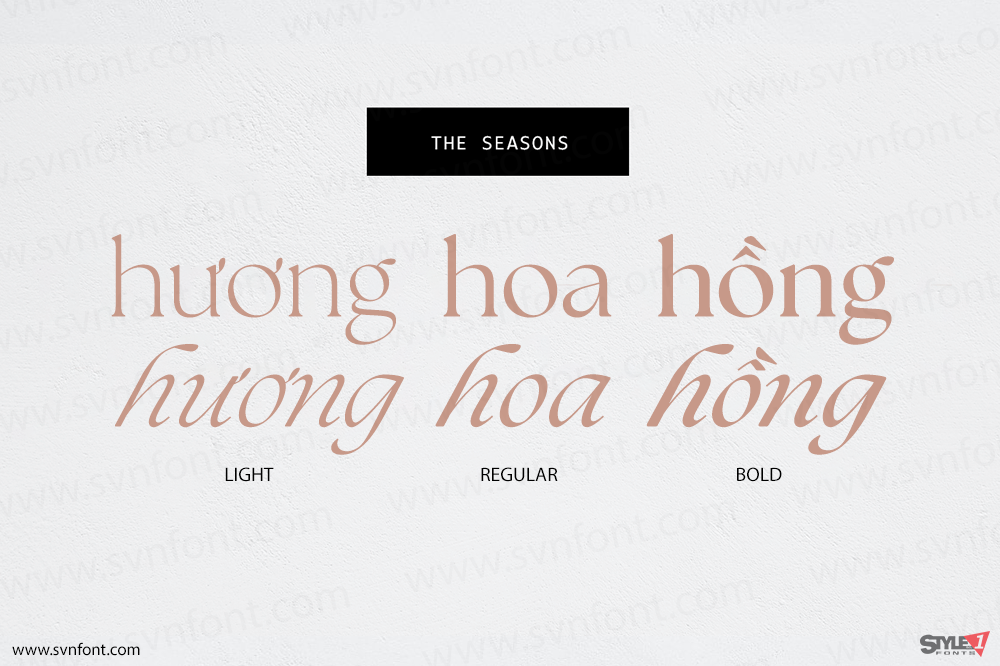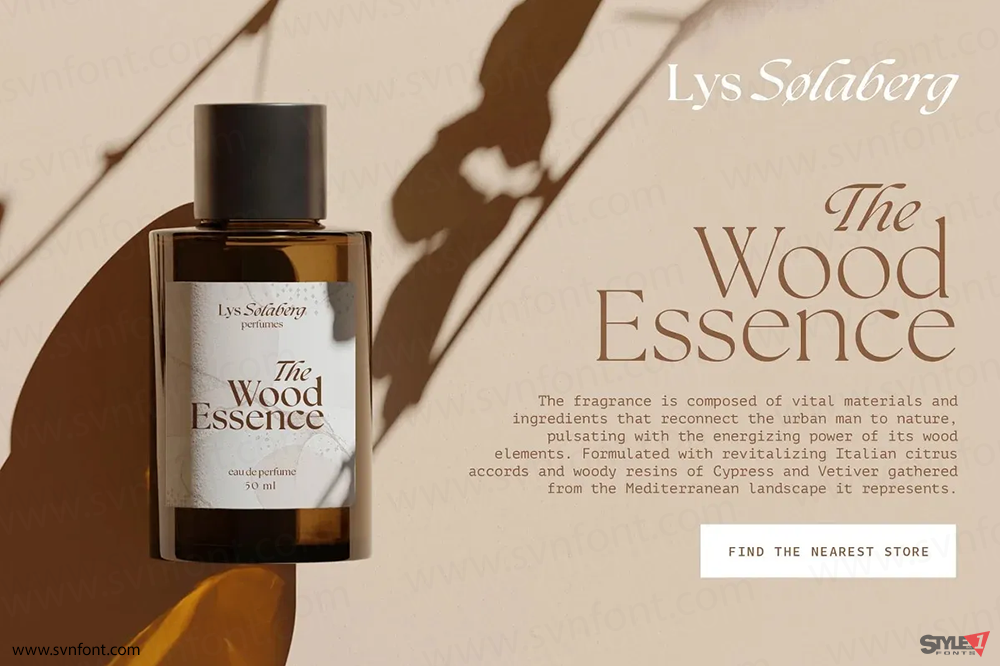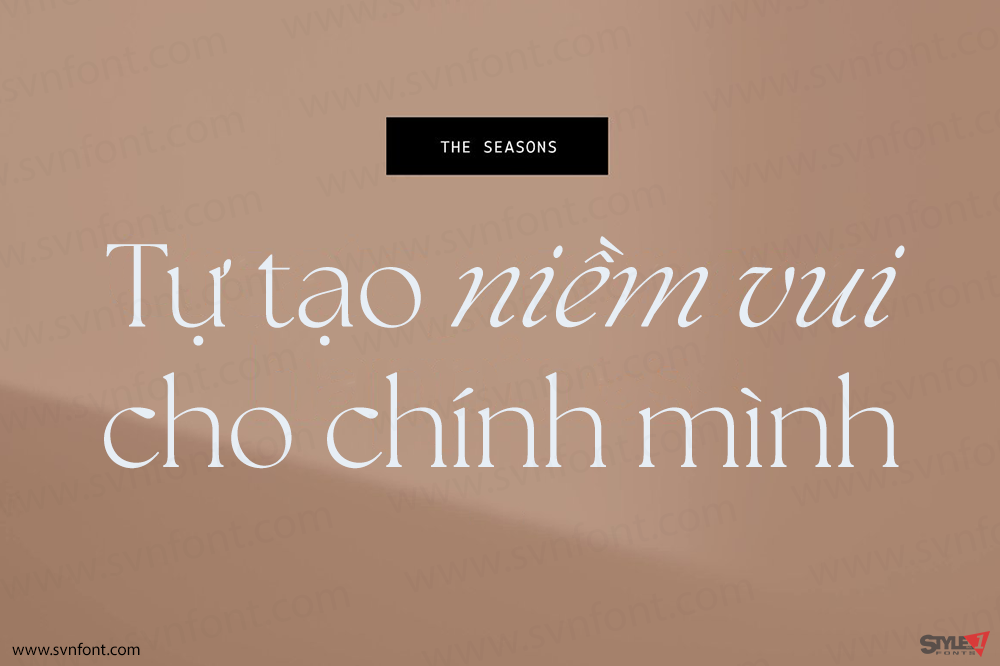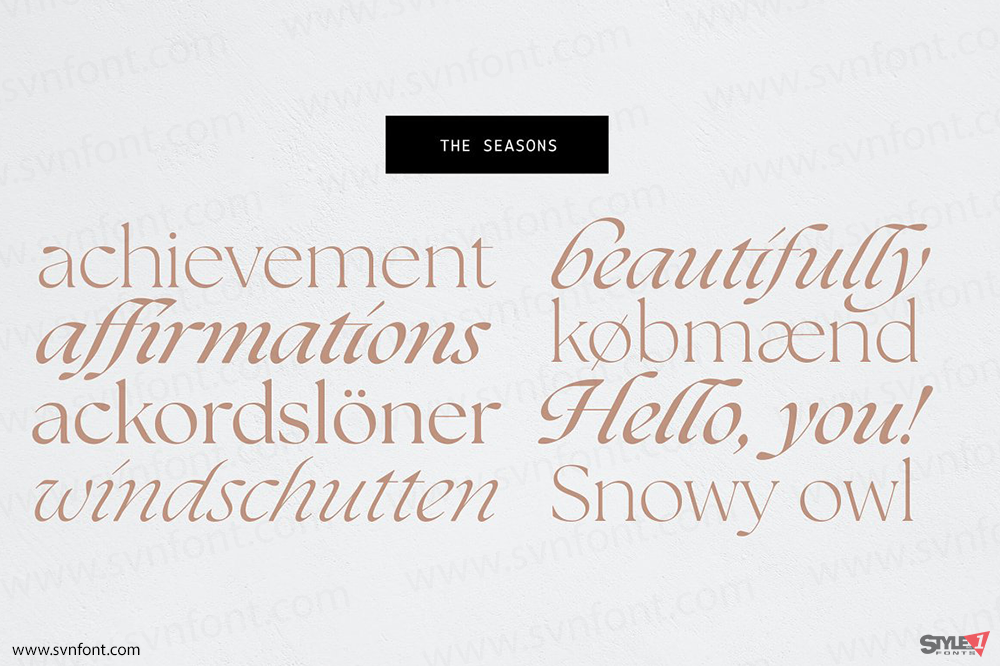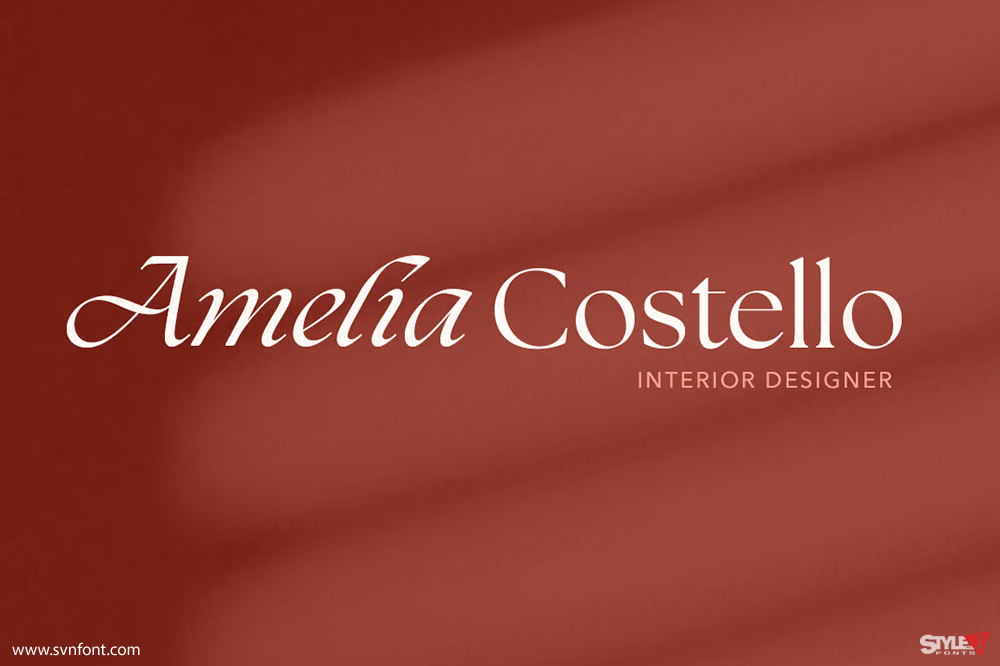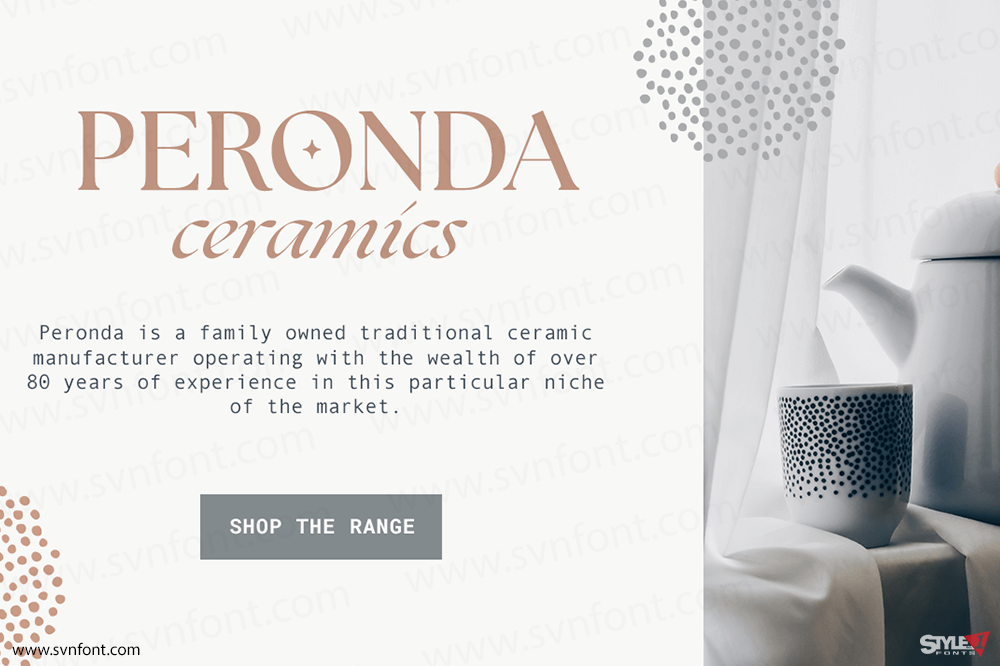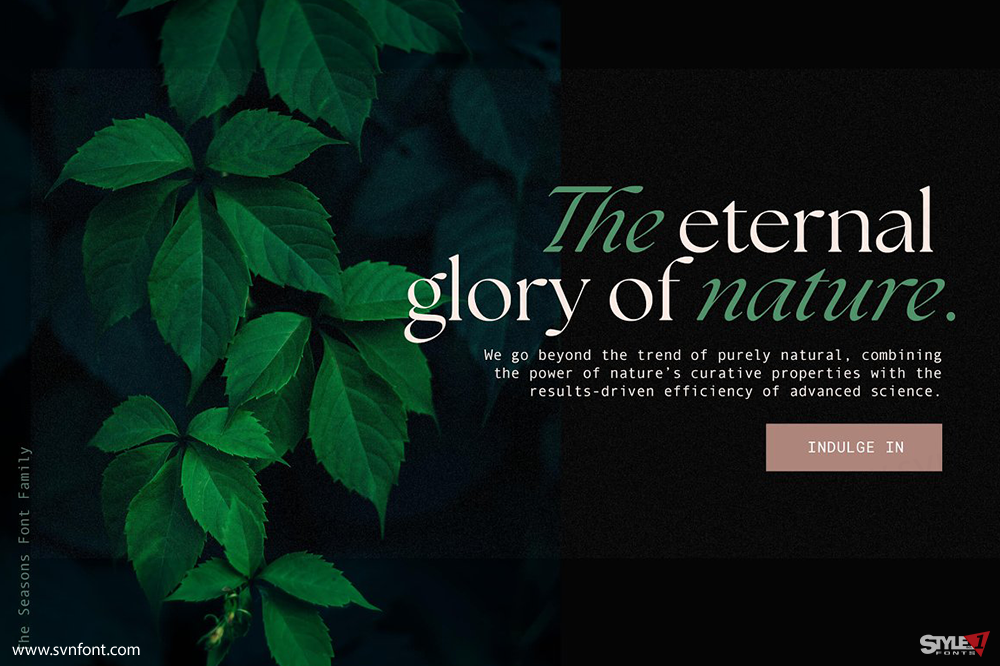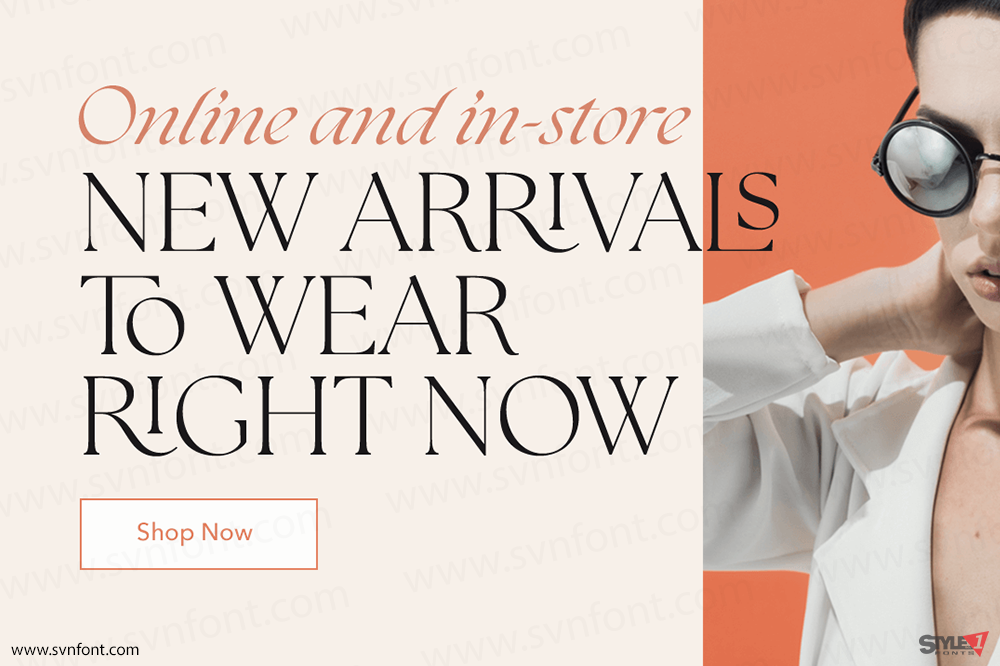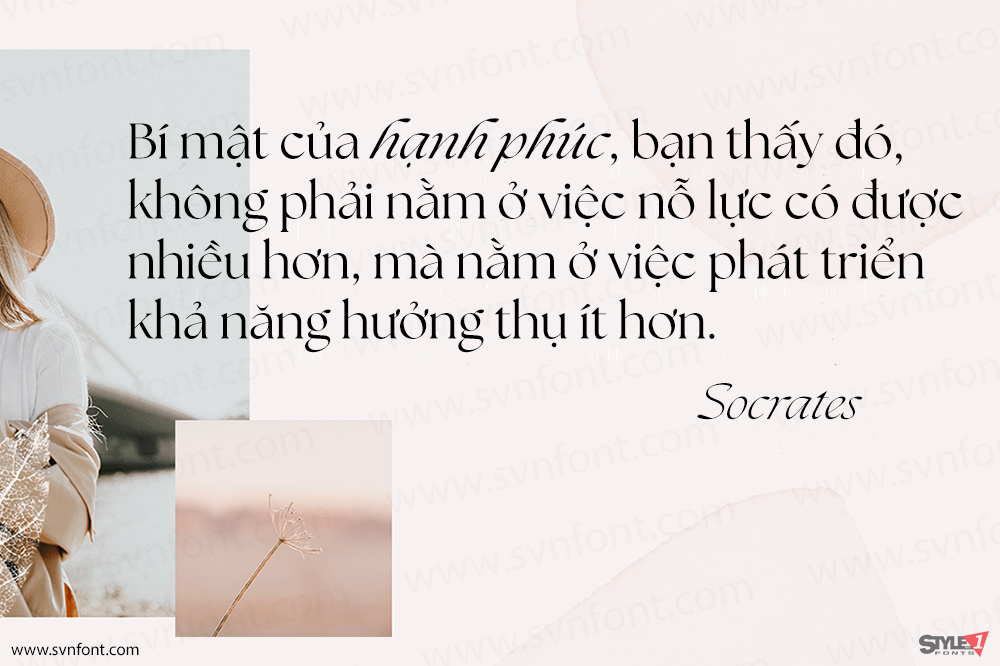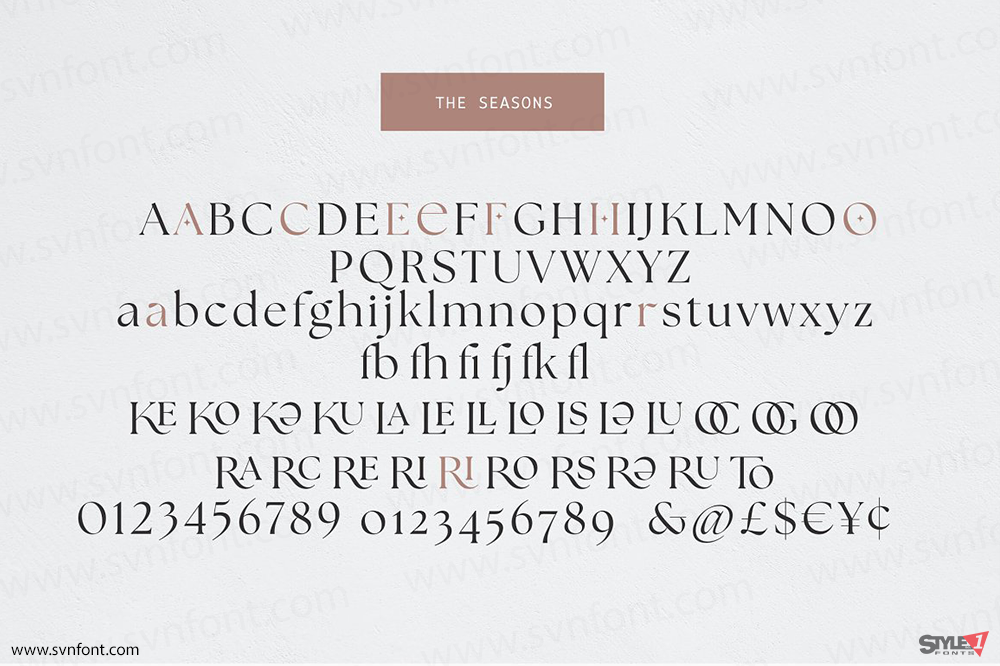
The Seasons là một họ font serif cổ điển thanh lịch bao gồm các font serif có độ tương phản cao với vẻ ngoài cổ điển sang trọng, cùng với các kiểu chữ nghiêng thư pháp (calligraphic cursive italics) tương ứng dựa trên một số kiểu chữ nghiêng nhân văn (humanistic italic scripts) và được viết bằng bút Pilot Parallel Pen.
Cả font chữ thẳng (upright) và nghiêng (italic) (tổng cộng 10 font) đều có chung kiểu chân chữ mềm (soft terminals) với đường cắt sắc nét và được tăng cường bởi các tính năng OpenType như nét nối (ligatures) và kiểu chữ thay thế (stylistic alternates).
The Seasons có thể được sử dụng trong xây dựng thương hiệu cao cấp, thiết kế logo, tạp chí, bao bì sản phẩm và thiệp mời.
Các tính năng opentype cũng được Việt hóa đầy đủ: kiểu thay thế, swash, ký tự ghép…